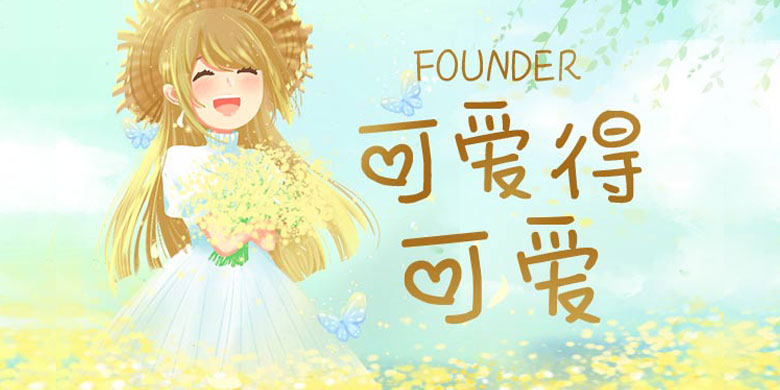
品牌:方正手迹设计师:刘晔发行时间:2020字库编码:大陆简体(GB2312-80)分类:创意书写字体属性:精品字
可爱得可爱这款字体打破常规,部件或放大或缩小,字形胖瘦变换,每个字都与众不同。口字旁做圆画处理,点画处理成爱心点缀中间,更添趣味。适用于青少儿漫画类的书刊、综艺字幕、品牌广告和产品包装设计,以及社交网络的个性化用字。